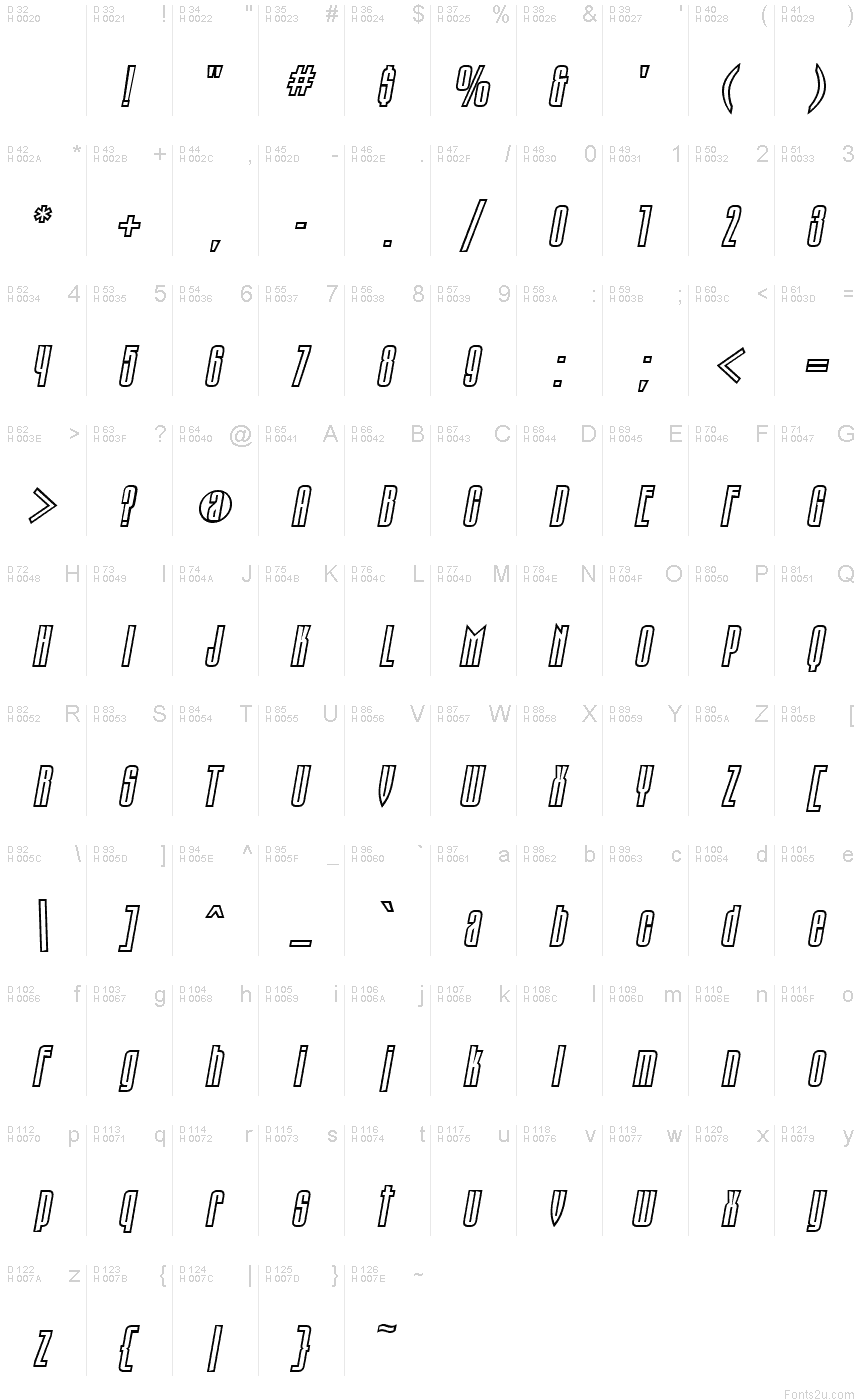
NK49 — это бесплатный кириллический дисплейный шрифт в гоночном стиле. Его высокие, наклоненные вперед буквы буквально созданы для скорости. Узкая форма, толстый внешний контур и светлая внутренняя линия создают ритм гоночного плаката, который остается выразительным даже при плотной верстке.
Он органично вписывается в спортивный брендинг, постеры автогонок, аркадные заголовки, афиши мероприятий и короткие надписи, где от бесплатного шрифта требуется движение, а не декоративность.
Используйте его для компактных заголовков, логотипов команд и быстрых монограмм — наклон и линейная обработка придают даже паре символов энергичный, скоростной вид.